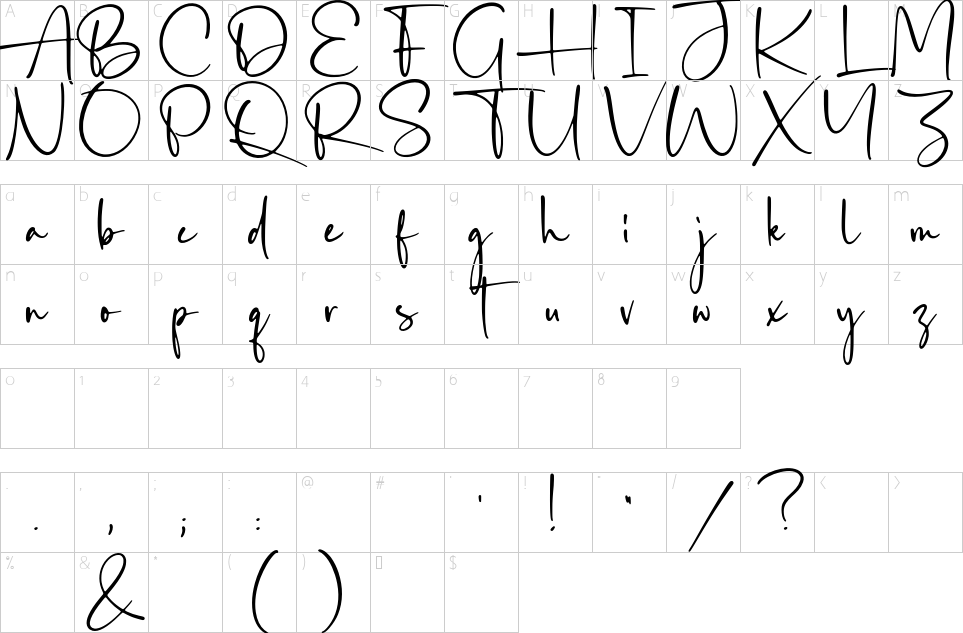
Acardia Font – Fonte Grátis
Acardia Font
Aguarda um instante, estou preparando uma descrição para você. Estou assim: Aguarda um instante, estou pronto para você. A fonte Acardia, disponível de forma gratuita para download tanto para Windows quanto para Mac, é uma criação da Letteralle Studios. Desde sua disponibilização, mais de duas mil e seiscentas pessoas já baixaram Acardia. Esta fonte não apenas oferece uma versatilidade sem igual, mas também um design elegante que se encaixa em diversos estilos de projetos gráficos. Se você está procurando por uma fonte de qualidade para seus projetos de design, Acardia pode ser uma ótima escolha. Com uma vasta gama de opções, esta fonte promete tornar o processo de criação ainda mais satisfatório.